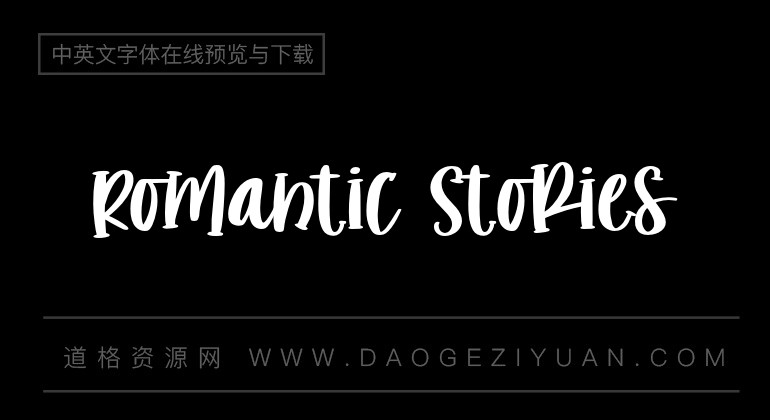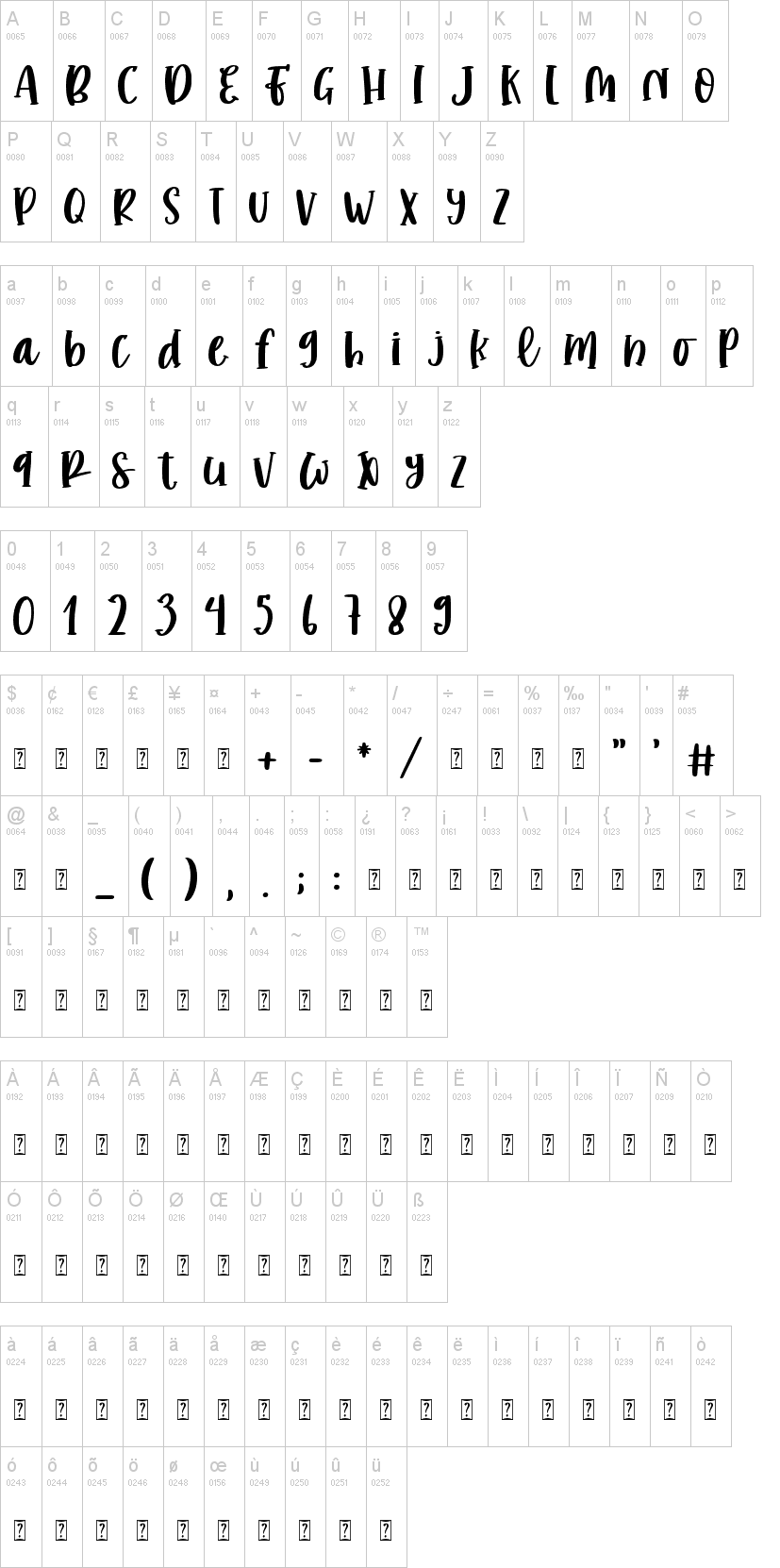
Romantic Stories
Romantic Stories是一种优美而流畅的手写风格字体。它具有优雅的线条和圆润的笔画,看起来非常温馨浪漫。 这种字体适用于很多场合,比如情人节贺卡、婚礼邀请函、手写信件、纪念册等等。它传达了温情脉脉的感觉,让人感到温馨、浪漫和亲切。 Romantic Stories字体的特点是它的字母间距和字母形状都非常平衡,这使得它非常易读和易于识别。同时,它的线条非常流畅,使得字体看起来非常舒适,仿佛是手写的一样。 总体来说,Romantic Stories是一种非常优美和浪漫的字体,适合用于传达温馨和亲密的感觉。
Romantic Stories是一款非常不错的手写艺术字体,具有很好的视觉感,适合于文化类的宣传设计、商业类品牌的广告和产品包装设计以及个性化文字排版等较多场景。
Romantic Stories字符映射图